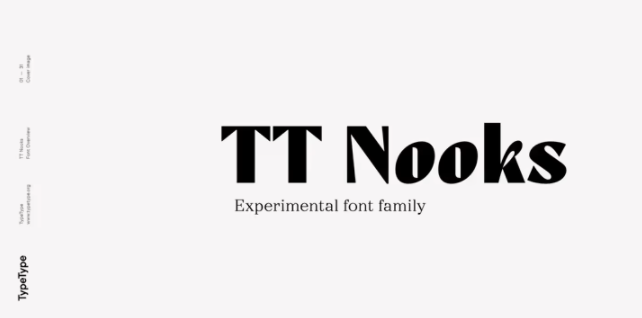
[Myfonts] TT Nooks Font (2021)
TT Nooks - это экспериментальное семейство шрифтов, которое включает в себя высококонтрастный засечный шрифт TT Nooks и вертикальный курсив TT Nooks Script. Несмотря на разницу в стиле, оба подсемейства хорошо уживаются друг с другом, что отчасти объясняется их схожими пропорциями. Каждое из подсемейств включает 4 начертания: Light, Regular, Bold и Black.
Основным подсемейством является TT Nooks - стильная высококонтрастная засечка с легким оттенком эгоцентризма. Если бы TT Nooks был человеком, то это была бы элегантная леди с независимым и твердым характером. В первоначальных эскизах TT Nooks присутствовали следы широкого пера, но в ходе дальнейшей эволюции шрифт отошел от этого стиля, сохранив лишь высокий контраст штрихов. Кроме того, в процессе дизайнерских поисков TT Nooks приобрел оттенок геометричности.
Засечки в TT Nooks особенно заметно выделяются благодаря своей геометрической форме, напоминающей тапочки. Помимо своей особенности, такие засечки придают шрифту устойчивость и позволяют лучше компенсировать соотношение черного и белого в буквах. TT Nooks имеет малые прописные буквы для латинского и кириллического алфавитов, а также набор стилистических альтернатив (включая некоторые фигуры), которые делают шрифт немного более геометричным. Кроме того, мы нарисовали более 25 лигатур, включая лигатуры для заглавных букв, косой ноль и множество других полезных функций OpenType.
TT Nooks Script - это дополнительное семейство, призванное гармонично дополнить основное семейство и расширить сферу его применения. Формы символов в полужирном и светлом шрифтах TT Nooks Script совершенно разные. Например, Black & Bold имеет высококонтрастные штрихи и открытое отверстие, а в Regular & Light отверстие символов закрыто. TT Nooks также имеет малые прописные буквы для латинского и кириллического алфавитов, лигатуры, фигуры старого стиля и другие особенности OpenType.
В светлых шрифтах TT Nooks Script более гуманистичен и имеет артефакты, присущие непрерывному движению плоского пера. В жирных шрифтах TT Nooks Script очень плотный и динамичный ритм набора, а форма букв начинает геометризироваться. Перед нами стояла сложная задача сохранить преемственность форм между жирным и светлым шрифтами, и нам удалось решить ее благодаря найденному ритму, объединившему разные шрифты, и близким стилистическим решениям.